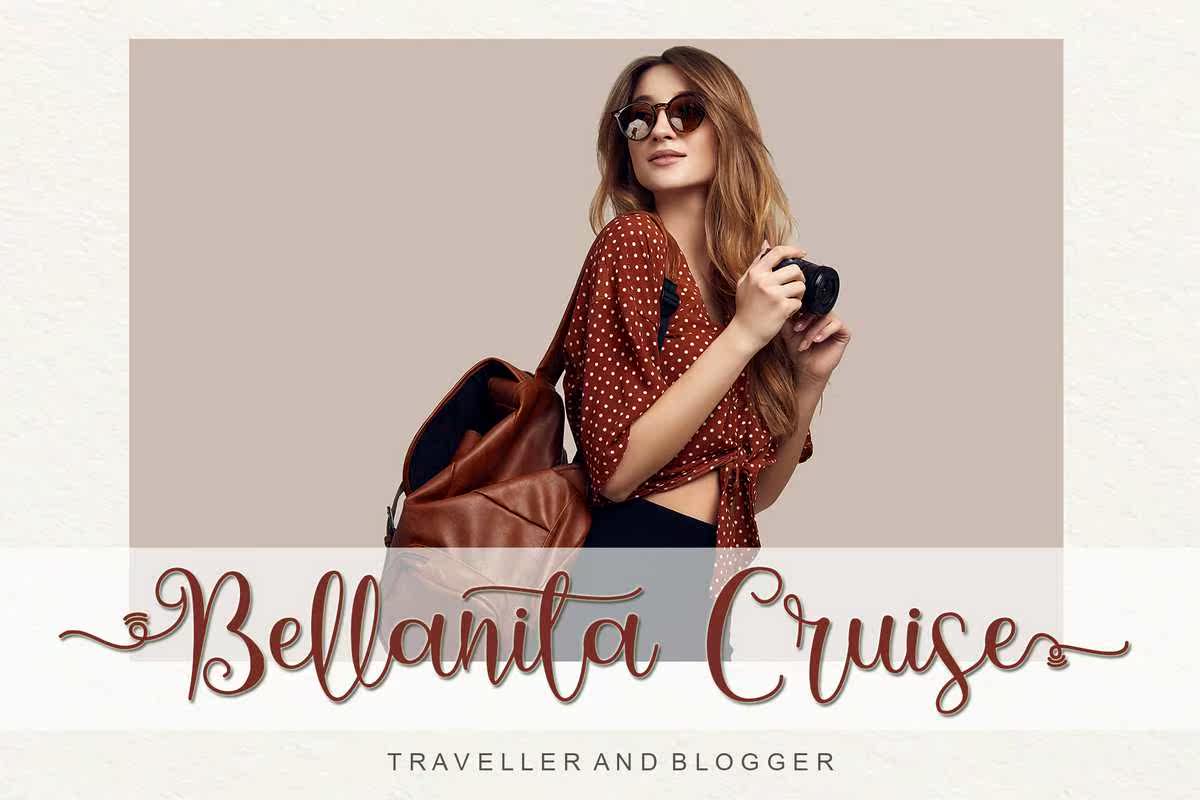
Warilahfont是一个现代化的AlligraphyFontByletraFastudio.Ithas Flowing Letters,它将为您的设计提供完美的解决方案;徽标、问候卡、包装设计、耐磨性、工艺设计、任何项目、书名、婚礼宣传、包装等。WARILAHFONT是一个现代化的AlligraphyFontBylettRafaStudio。它具有流动的字母,将使您的设计更加完美。WARILAHFONT;徽标、问候卡、包装设计、耐磨性、工艺设计、任何项目、书名、婚礼宣传、包装等。